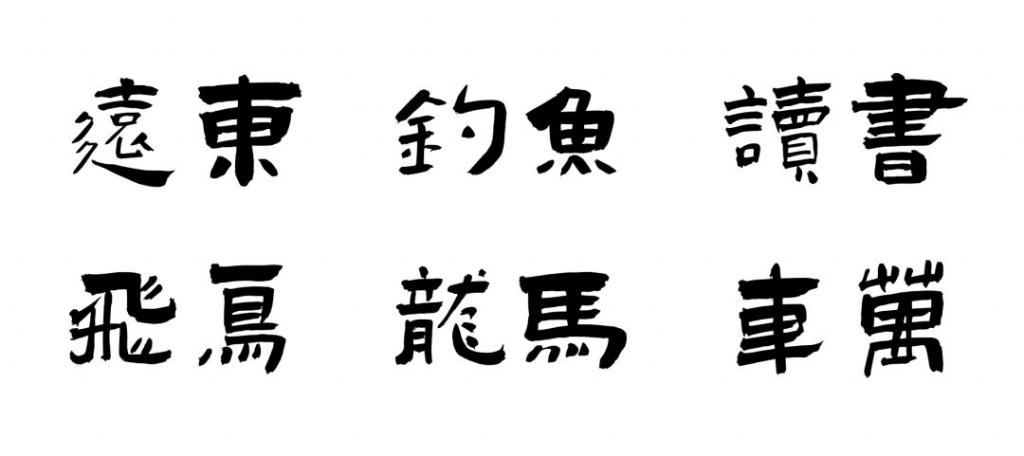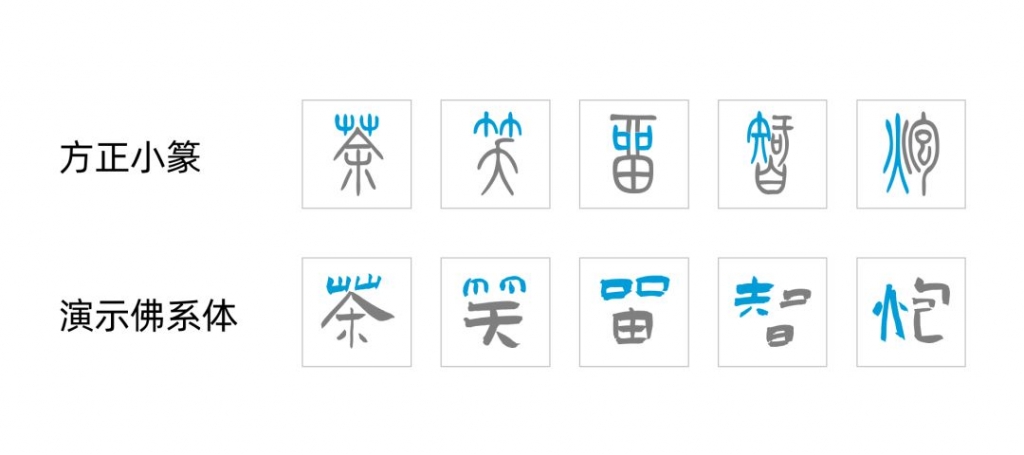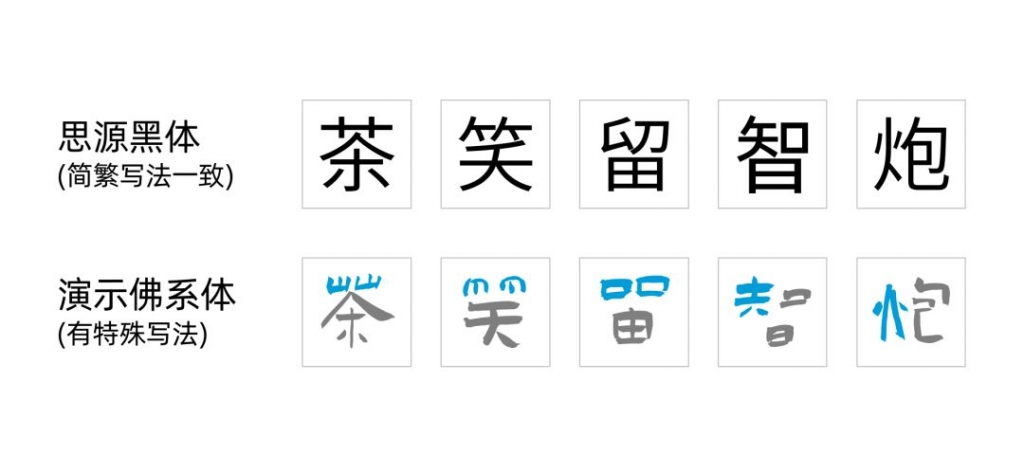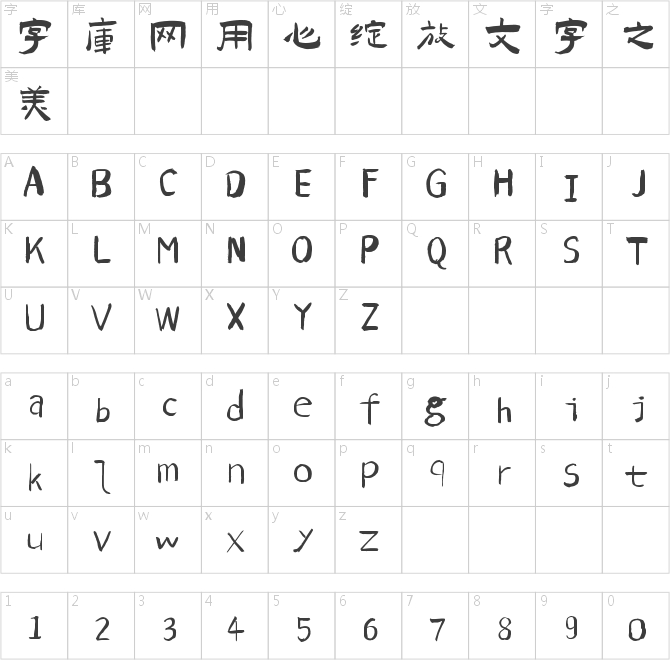
字體名稱(chēng): 演示佛系體
演示佛系體是一款風(fēng)格十分特別的字體,紀(jì)國(guó)才老先生一生酷愛(ài)書(shū)法,在80歲這年親手寫(xiě)了一套獨(dú)具風(fēng)格的字體,這套字體看似隨意,但是蘊(yùn)含著老先生一生的閱歷和經(jīng)驗(yàn),隨意之中又帶點(diǎn)不隨意。
字體整體乍看之下,似以繁體字為主。但多看一些,才發(fā)現(xiàn),諸多奇特的偏旁部首寫(xiě)法,是現(xiàn)代簡(jiǎn)體繁體都不具備的。
一位練習(xí)書(shū)法多年的老先生,難道會(huì)標(biāo)新立異自創(chuàng)寫(xiě)法嗎? 實(shí)際恰好相反,我們需要到更加古老的字體中尋找答案——「演示佛系體」許多寫(xiě)法與小篆類(lèi)似。
關(guān)于紀(jì)國(guó)才先生
出生于1939年的紀(jì)老先生,已過(guò)杖朝之年。一生經(jīng)歷了風(fēng)云更迭,字如其人,印刻著時(shí)光的痕跡,沉淀著歲月的厚重,也訴說(shuō)著人生的灑脫,有種超然物外之態(tài)。
(字體原稿作者:紀(jì)國(guó)才老先生)